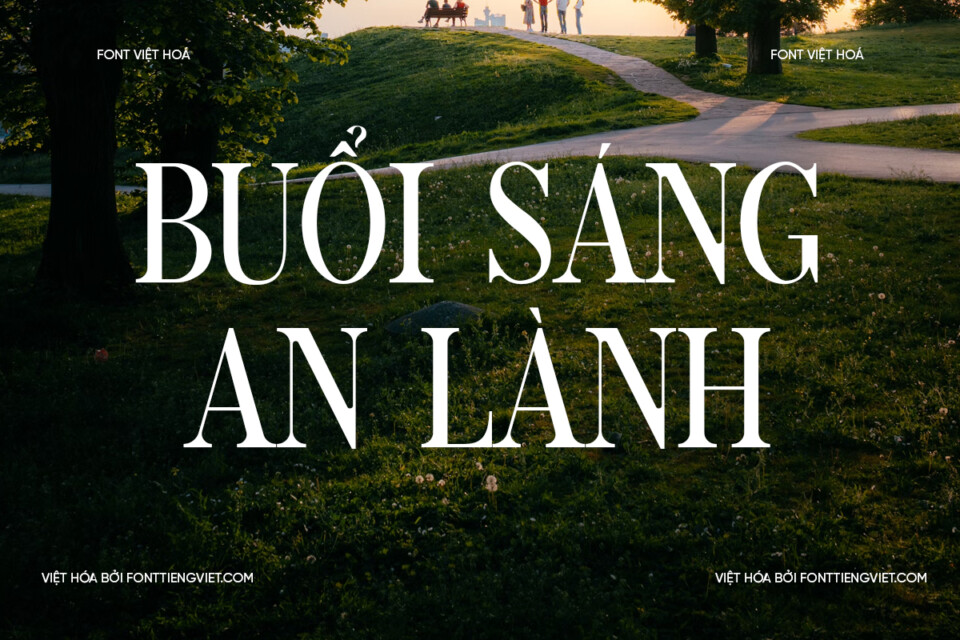
Font Việt hóa 1FTV VIP Morgan
Giới thiệu về Font Việt hóa 1FTV VIP Morgan trong thiết kế đồ họa
Trong thế giới thiết kế hiện đại, việc lựa chọn một bộ phông chữ phù hợp đóng vai trò quyết định đến sự thành công của một tác phẩm nghệ thuật. Font Việt hóa 1FTV VIP Morgan nổi lên như một lựa chọn hàng đầu cho những ai yêu thích phong cách sang trọng, thanh lịch nhưng không kém phần trẻ trung. Đây là một bộ Font Miễn Phí đã được tinh chỉnh kỹ lưỡng về dấu tiếng Việt, giúp các bạn học sinh, sinh viên và những người làm thiết kế không chuyên dễ dàng áp dụng vào các dự án học tập hay sáng tạo cá nhân. Với đường nét sắc sảo và độ tương phản tinh tế, bộ font này mang lại cảm giác chuyên nghiệp ngay từ cái nhìn đầu tiên. Việc sử dụng các phông chữ đã được Việt hóa giúp chúng ta tránh được lỗi hiển thị dấu vốn rất phổ biến ở các font nguyên bản nước ngoài.
Những đặc điểm nổi bật của Font Việt hóa 1FTV VIP Morgan
Thiết kế hiện đại và linh hoạt
Bộ Font Việt hóa 1FTV VIP Morgan sở hữu cấu trúc chữ cái cân đối, với các nét thanh nét đậm được xử lý mượt mà. Điều này giúp bộ font không chỉ phù hợp cho các tiêu đề lớn mà còn hiển thị rõ nét trong các đoạn văn bản ngắn. Đối với các bạn học sinh, việc dùng font chữ này để làm slide thuyết trình hay thiết kế bìa báo tường sẽ tạo nên một diện mạo hoàn toàn mới, bắt mắt và đầy tính thẩm mỹ. Sự linh hoạt của nó cho phép người dùng kết hợp với nhiều phong cách khác nhau từ cổ điển đến tối giản.
Tối ưu hóa cho người dùng Việt Nam
Một trong những điểm cộng lớn nhất là bộ font này đã được các chuyên gia từ 1FTV thực hiện Việt hóa tỉ mỉ. Các dấu thanh như huyền, sắc, hỏi, ngã, nặng được đặt ở vị trí chuẩn xác, không bị đè lên chữ hay gây cảm giác rối mắt. Điều này cực kỳ quan trọng trong giáo dục và thiết kế chuyên nghiệp, nơi sự rõ ràng của văn bản là ưu tiên hàng đầu. Font Việt hóa 1FTV VIP Morgan đảm bảo rằng mọi thông điệp bạn muốn truyền tải đều được thể hiện một cách trọn vẹn và đẹp mắt nhất.
Ứng dụng thực tế của bộ font trong học tập và công việc
Bạn có thể ứng dụng Font Việt hóa 1FTV VIP Morgan vào rất nhiều mục đích khác nhau. Trong môi trường học đường, bộ font này rất lý tưởng để làm tiêu đề cho các bài tiểu luận, thiết kế thiệp mời sự kiện trường học hoặc tạo các poster cổ động. Trong công việc kinh doanh nhỏ, nó có thể dùng làm logo hoặc nhận diện thương hiệu cho các thương hiệu thời trang, mỹ phẩm nhờ vẻ ngoài cao cấp. Khả năng tương thích tốt với các phần mềm thiết kế phổ biến như Photoshop, Illustrator hay thậm chí là Canva và Word giúp việc sử dụng trở nên cực kỳ đơn giản.
Cách cài đặt và sử dụng Font Việt hóa 1FTV VIP Morgan hiệu quả
Lời kết về bộ Font Việt hóa 1FTV VIP Morgan